크리스마스
The Christmas는 명절 디자인에 축제 느낌을 더하기에 완벽한 대조를 이루는 훌륭한 글꼴입니다. 장식 글꼴인 Decohead Display와 단순하고 우아한 산세리프 글꼴인 Hubhead를 사용하여 이 듀오는 다재다능함과 스타일을 제공합니다.
Decohead Display는 3가지 두께로 제공되며 표준 라틴어 스크립트 지원과 함께 대문자 및 소문자를 특징으로 합니다. 반면에 Hubhead는 대문자와 소문자가 있고 광범위한 라틴 스크립트 언어를 지원하는 원 웨이트 글꼴입니다.
명절 카드, 파티 초대장 또는 기타 축제 프로젝트를 디자인할 때 이 명랑하고 밝은 듀오는 화려함과 우아함을 더할 것입니다. 모두에게 메리 크리스마스!
크리스마스 모차르트
크리스마스 디자인 프로젝트를 향상시킬 완벽한 글꼴을 찾고 계십니까? 크리스마스 모차르트보다 더 이상 보지 마십시오! 이 축제 세리프 글꼴은 독창성, 상상력 및 끝없는 재미를 돋보이게 하고 영감을 주기 위해 디자인되었습니다.
통통 튀는 캘리그라피 스타일에서 영감을 받은 크리스마스 모차르트는 모든 디자인에 유쾌한 터치를 더합니다. 그것의 미적 매력은 책 표지, 포스터, 포장, 상품, 로고 등에 대한 훌륭한 선택입니다.
Christmas Mozart를 사용하면 크리스마스 분위기를 담은 멋진 영상을 만들 수 있습니다. 이 글꼴은 디자인을 더욱 매력적이고 눈길을 사로잡도록 해줍니다. 그래서 왜 기다려? 이번 크리스마스 시즌에 크리스마스 모차르트를 들고 창의력을 발휘해 보세요.
크리스마스 이야기
Story of Christmas는 휴일 디자인에 축제 분위기를 더해줄 글꼴입니다. 300개가 넘는 글리프를 사용하여 Swash, Stylistic Sets, Stylistic Alternates 및 Contextual Alternates와 같은 Open Type 기능을 통해 다양한 대체 문자를 제공합니다.
즉, 다양한 문자 변형에 액세스하여 프로젝트를 향상시킬 수 있습니다. Adobe Illustrator, Adobe InDesign, Adobe Photoshop Corel Draw 및 Microsoft Word와 같은 인기 있는 디자인 프로그램에서 이 글꼴을 사용할 수 있습니다.
특별히 코딩된 PUA 유니코드 덕분에 모든 대체 문자는 장인과 디자이너 모두 쉽게 액세스할 수 있습니다.
따라서 크리스마스 카드, 연휴 전단 또는 계절 포스터를 제작하든 관계없이 Story of Christmas는 디자인에 매력과 축제 분위기를 더할 것입니다.
퍼플 크리스마스
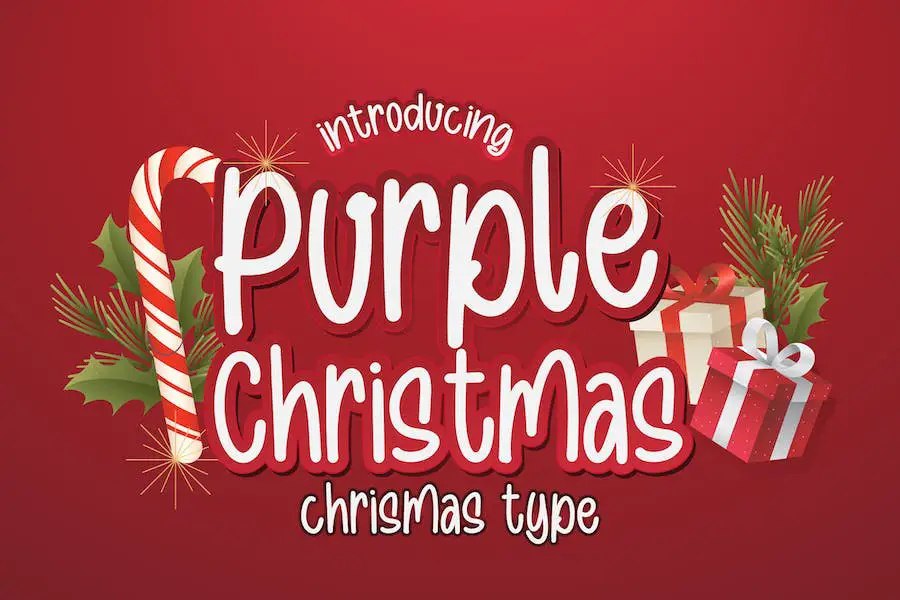
Purple Christmas는 친근하고 우아한 디스플레이 글꼴로 휴일 테마 연하장과 공예 프로젝트에 신선하고 풍부한 느낌을 더합니다. 낭만적인 분위기는 휴가 시즌의 정신을 포착하는 축제 디자인을 만들기에 완벽합니다.
고유한 스타일과 다재다능한 이 글꼴은 우아함과 매력으로 프로젝트를 향상시키려는 그래픽 디자이너에게 탁월한 선택입니다. 퍼플 크리스마스로 깊은 인상을 남길 준비를 하고 휴일의 마법을 구현하는 멋진 디자인을 만드세요.
매직 크리스마스
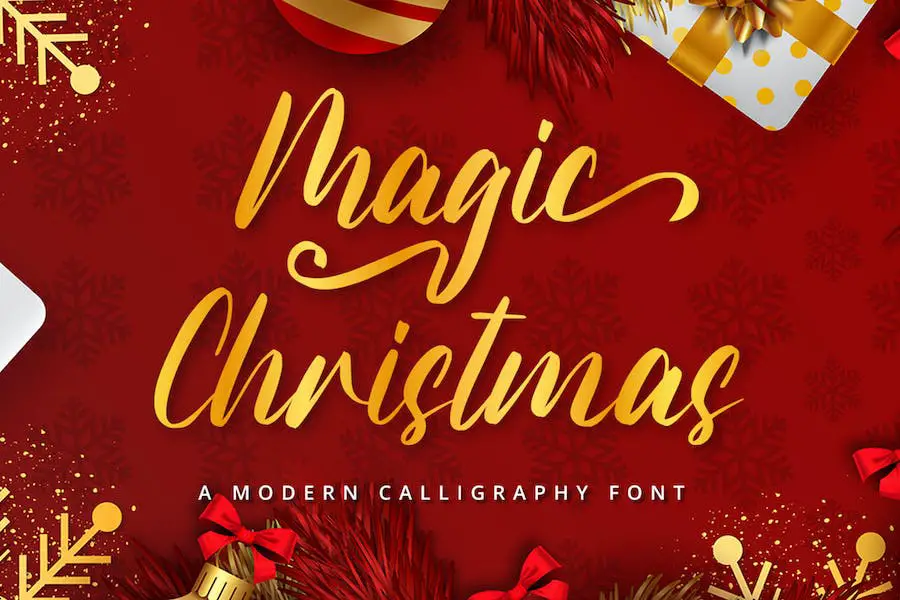
Magic Christmas는 휴가 프로젝트에 우아함을 더해주는 멋진 손글씨 글꼴입니다. 풍부하고 따뜻한 디자인으로 축제 연하장을 만들거나 모든 공예 노력에 아늑한 느낌을 더하는 데 적합합니다.
글꼴은 PUA로 인코딩되어 모든 고유한 글리프 및 스와시에 쉽게 액세스할 수 있습니다. 디자인에 생명을 불어넣을 크리스마스 글꼴을 찾고 있다면 Magic Christmas가 완벽한 선택입니다. 이 아름다운 글꼴로 휴가 창작물을 빛나게 할 준비를 하세요!
간단한 크리스마스
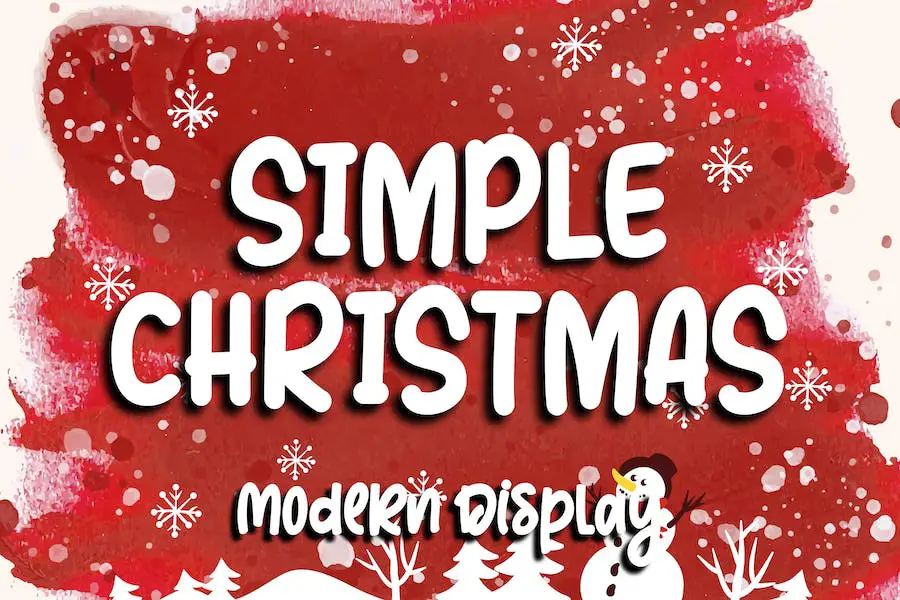
Simple Christmas는 모든 축제 휴가 디자인을 위한 환상적인 글꼴입니다. 대담하고 재미있고 재미있기 때문에 만화 관련 프로젝트, 어린이 게임 또는 사랑스러운 터치가 필요한 창작물에 적합합니다.
이 글꼴을 밝은 색상과 결합하면 아이디어에 생명을 불어넣고 멋진 디자인을 만드는 데 도움이 됩니다. 또한 이 글꼴은 PUA로 인코딩되어 있기 때문에 모든 아름다운 글리프에 매우 쉽게 액세스할 수 있습니다. 그래서 왜 기다려? Simple Christmas로 프로젝트에 휴가 분위기를 더하세요!
크리스마스 우아한
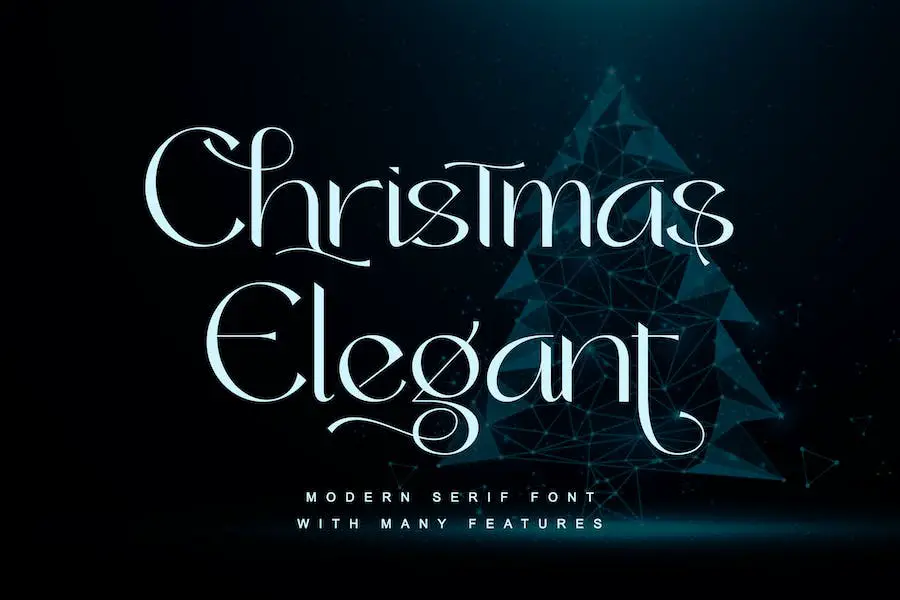
Christmas Elegant는 축제 휴가 디자인에 우아함을 더하는 데 완벽한 멋진 세리프 서체입니다. 모던하고 클래식한 스타일의 이 글꼴은 여러분의 프로젝트를 빛나게 해 줄 것입니다.
독특하고 화려한 분위기에 푹 빠지고 멋진 디자인을 만드는 데 사용할 때 창의력을 발휘하십시오. 또한 글꼴은 PUA로 인코딩되어 모든 글리프에 액세스하고 무한한 가능성을 열 수 있습니다.
명절 카드, 초대장, 심지어 문신 디자인 작업을 하든 Christmas Elegant는 글꼴 컬렉션에 꼭 추가해야 할 필수품입니다. 따라서 이 놀라운 글꼴로 연말 연시 분위기를 퍼뜨릴 준비를 하세요!
크리스마스 희망
Christmas Hopeful은 모든 디자인 요구 사항, 특히 크리스마스 테마 및 공예와 관련된 요구 사항에 완벽한 스크립트 듀오 글꼴입니다. 소셜 미디어 게시물, 인용구, 이미지 오버레이, 슬로건 로고, 포스터, 인쇄물, 웹사이트 배너 등과 같은 다양한 프로젝트에 사용할 수 있습니다.
독특하고 축제적인 스타일의 Christmas Hopeful은 모든 프로젝트에 명절 분위기를 더해줍니다.
글꼴의 속성에는 우아함과 매력을 발산하는 아름다운 스크립트 스타일이 포함됩니다. 그것의 곡선과 복잡한 디테일은 휴가 시즌의 본질을 포착하여 멋진 디자인을 만드는 데 이상적입니다.
크리스마스 인사말 카드를 디자인하든 축제 웹사이트 배너를 디자인하든 Christmas Hopeful은 확실히 프로젝트를 돋보이게 만들 것입니다.
크리스마스 눈송이 딩뱃
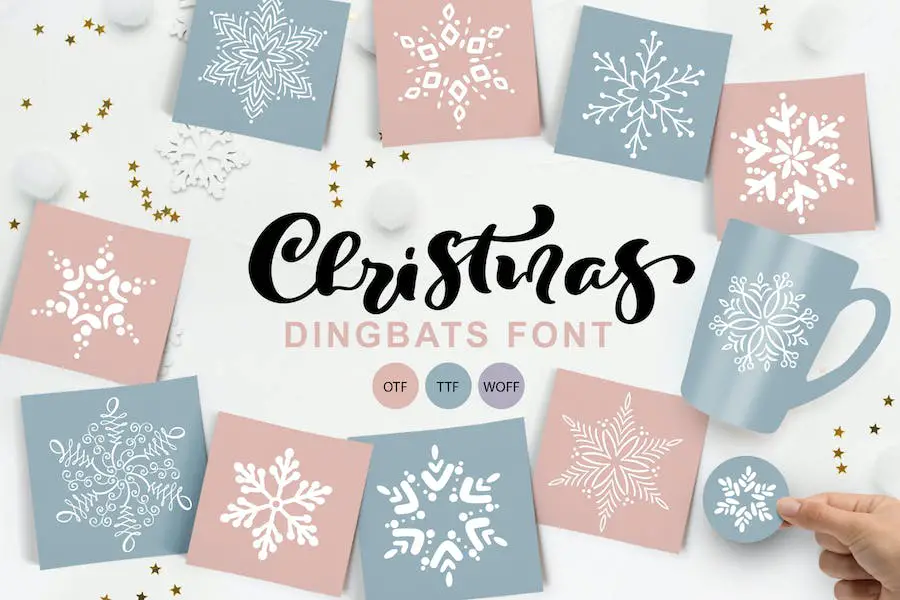
Christmas Snowflake Dingbats는 휴일 테마 프로젝트를 향상시키려는 그래픽 디자이너와 블로거를 위한 환상적인 글꼴입니다.
손으로 그린 낙서 기호로 모든 디자인에 매력을 더합니다. 이 글꼴은 스칸디나비아 또는 휘게 스타일을 수용하는 사람들에게 특히 좋습니다.
Christmas Snowflake Dingbats의 가장 좋은 점 중 하나는 사용 편의성입니다. 이 아름다운 기호에 액세스하기 위해 추가 프로그램이 필요하지 않습니다. 소문자, 대문자 및 숫자를 포함하여 일반 키보드 키에 단순히 매핑됩니다.
글꼴을 설치하고 입력을 시작하고 창의력을 발휘하기만 하면 됩니다!
이 글꼴은 축제 휴일 디자인을 만드는 데 적합합니다. 크리스마스 카드에 명랑한 눈송이 악센트를 추가하거나 독특한 소셜 미디어 그래픽을 만들고 싶다면 Christmas Snowflake Dingbats가 도와드립니다.
덕분에 휴가 분위기를 작업에 쉽게 통합할 수 있습니다.
아버지 크리스마스
Father Christmas는 축제 시즌의 분위기를 담아낸 유쾌한 손글씨 서체입니다. 신선하고 우아한 스타일로 크리스마스 테마 인사말 카드, 브랜딩 자료, 명함, 인용구, 포스터 등을 만드는 데 적합합니다.
이 글꼴은 PUA로 인코딩되어 제공되는 모든 놀라운 글리프 및 스와시에 쉽게 액세스할 수 있습니다. 또한 대체 글리프 및 합자와 같은 다양한 특수 기능이 함께 제공되어 디자인에 창의성을 더할 수 있습니다.
Father Christmas를 사용하면 프로젝트에 명절 분위기를 더할 수 있습니다. 그것의 축제적이고 풍부한 미학은 모든 디자인에 즉시 기쁨과 따뜻함을 더합니다.
사랑하는 사람을 위한 크리스마스 카드를 만들거나 비즈니스를 위한 홍보 자료를 디자인할 때 이 글꼴은 환상적인 선택입니다.
가디건 크리스마스
Cardigan Christmas는 디자인에 사랑과 현대성을 더하는 섬세하고 우아한 손글씨 글꼴입니다. 부드러운 선과 다양한 기준선이 있는 이 글꼴은 제목, 결혼식, 초대장, 서명, 로고 등에 적합합니다.
아름답고 균형 잡힌 캐릭터를 가지고 있어 다양한 디자인에 다용도로 사용할 수 있습니다. 포스터, 배지 또는 브랜딩 자료를 만들 때 Cardigan Christmas는 창의적인 아이디어를 실현할 것입니다. 이 아름다운 글꼴로 프로젝트에 축제 분위기와 스타일리시한 느낌을 더하세요.
카디건 크리스마스를 명절 디자인과 함께 사용하고 크리스마스 시즌 동안 즐겁고 즐거운 분위기를 조성하는 것이 좋습니다. 현대적이고 유려한 스타일은 모든 프로젝트에 우아함과 세련미를 더합니다.
명절 카드, 파티 초대장 또는 기타 계절 자료를 디자인하든 관계없이 이 글꼴은 깊은 인상을 남길 것입니다.
크리스마스 라운지
Christmas Lounge는 일반 및 기울기의 두 가지 스타일로 제공되는 환상적인 디스플레이 서체입니다. 멋진 캐릭터와 독특한 디자인을 갖춘 이 글꼴은 프로젝트를 향상시키는 데 적합합니다.
명함, 포스터, 로고, 잡지, 표지, 배너, 티셔츠, 머리글 또는 대규모 아트워크에 필요한 것이 무엇이든 크리스마스 라운지에서 해결해 드립니다. 모든 디자인에 기쁨을 가져다 줄 다재다능한 글꼴로 축제 분위기를 느껴보세요.
유쾌한 Christmas Lounge 글꼴로 창의력을 발휘하고 프로젝트를 돋보이게 만드세요.
해피 크리스마스 파티
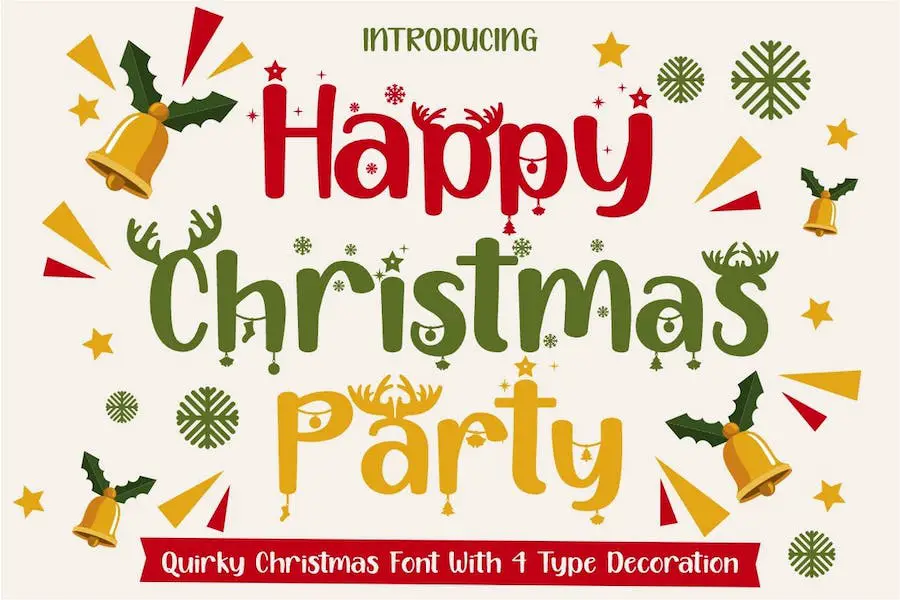
Happy Christmas Party는 홀리데이 시즌을 위해 특별히 디자인된 즐겁고 기발한 디스플레이 글꼴입니다. 일반, 장식, 사슴, 눈, 별 등 5가지 고유한 장식 버전이 있는 이 글꼴은 모든 크리스마스 테마 프로젝트에 완벽한 축제 분위기를 선사합니다.
눈길을 끄는 기프트 카드나 이벤트 초대장을 만들려는 공예가, 독특한 로고타입이나 포장 디자인이 필요한 디자이너라면 이 글꼴을 사용할 수 있습니다.
또한 매우 다재다능하고 다국어를 지원하므로 광범위한 프로젝트에 적합합니다. 해피 크리스마스 파티로 디자인에 크리스마스 마법을 더해보세요!
팔
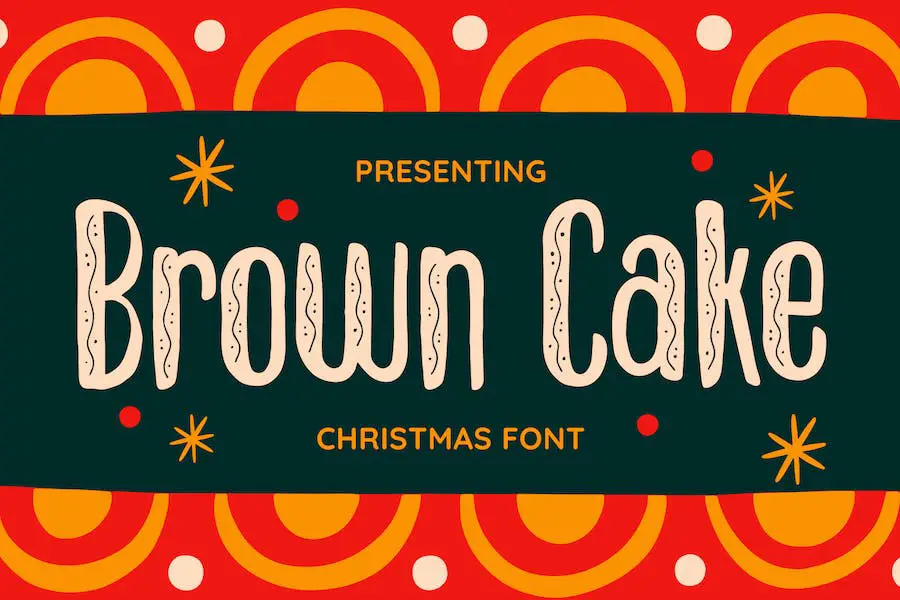
Boom은 휴일 디자인에 축제 분위기를 더하기에 완벽한 멋진 글꼴입니다. 이 글꼴은 매우 다양하며 로고, 브랜딩, 책, 티셔츠, 잡지 등에 사용할 수 있습니다. 시선을 사로잡는 헤드라인과 인사말을 만들기 위한 이상적인 선택입니다.
대문자와 소문자, 숫자와 문장 부호의 조합, 다국어 지원, 개방형 기능을 통해 멋진 디자인을 만드는 데 필요한 모든 도구를 사용할 수 있습니다.
또한 이 글꼴은 다른 글꼴과 아름답게 결합되어 독특하고 응집력 있는 모양을 만들 수 있습니다. Boom으로 프로젝트에 크리스마스 마법을 더할 수 있는 기회를 놓치지 마세요!
사탕
Candy는 그래픽 디자인 프로젝트에 축제 분위기를 더해줄 유쾌한 크리스마스 글꼴입니다. 캘리그라피의 아름다움에서 영감을 받은 이 글꼴은 눈길을 끄는 디스플레이 제작, 티셔츠 디자인, 제작, 인용 부호 제작 및 독특한 로고 제작에 적합합니다.
재미있는 테마와 우아한 스타일을 갖춘 Candy는 휴일 디자인에 장난스럽고 축제적인 분위기를 더할 수 있는 완벽한 선택입니다.
당신이 전문 그래픽 디자이너이거나 휴가철에 솜씨를 발휘하는 것을 즐긴다면, Candy는 당신의 프로젝트에 특별한 터치를 더하기 위한 필수 글꼴입니다.
아나이라
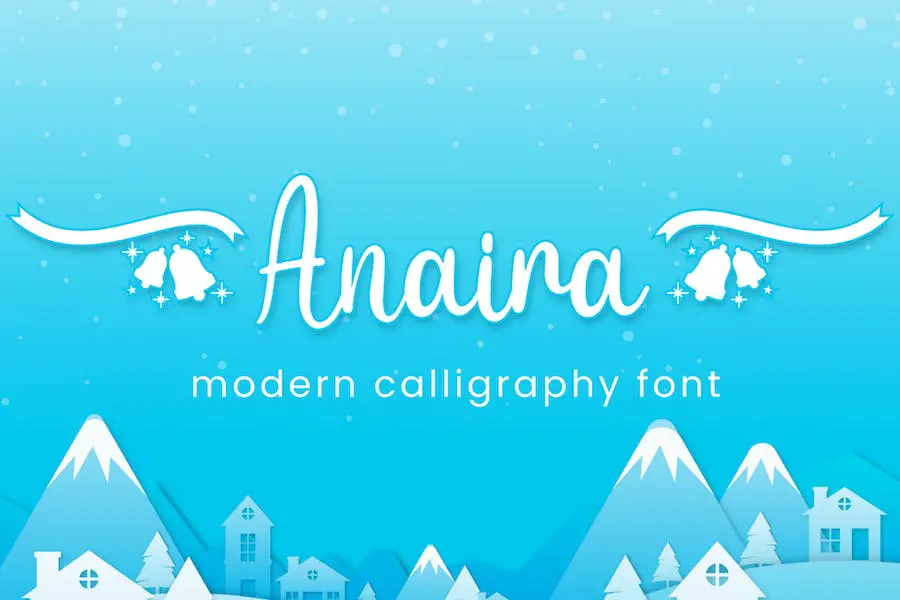
Anaira는 매력적인 벨과 리본 땡땡이 함께 제공되는 아름답고 독특한 손글씨 글꼴입니다. 이 글꼴은 모든 크리스마스 홍보 자료 및 디자인에 이상적입니다.
다양한 기능을 통해 브랜딩, 로고, 초대장, 편지지, 소셜 미디어 게시물, 제품 포장 등을 위한 멋진 그래픽을 만들 수 있습니다.
귀엽고 유쾌한 스타일의 Anaira는 게임 제목, 블로그 디자인, 책 및 표지 제목 및 크리스마스 분위기가 필요한 기타 프로젝트에 적합합니다.
Anaira의 섬세하고 뚜렷한 손글씨는 당신의 시선을 즉시 사로잡을 것입니다. 종과 리본이 특징인 딩뱃 캐릭터는 디자인에 축제 분위기를 더해줍니다.
명절을 주제로 한 로고를 만들거나 크리스마스 세일을 홍보하기 위해 소셜 미디어 게시물을 만들 때 Anaira는 당신의 디자인을 돋보이게 할 독특한 매력을 더할 것입니다.
써니 크리스마스
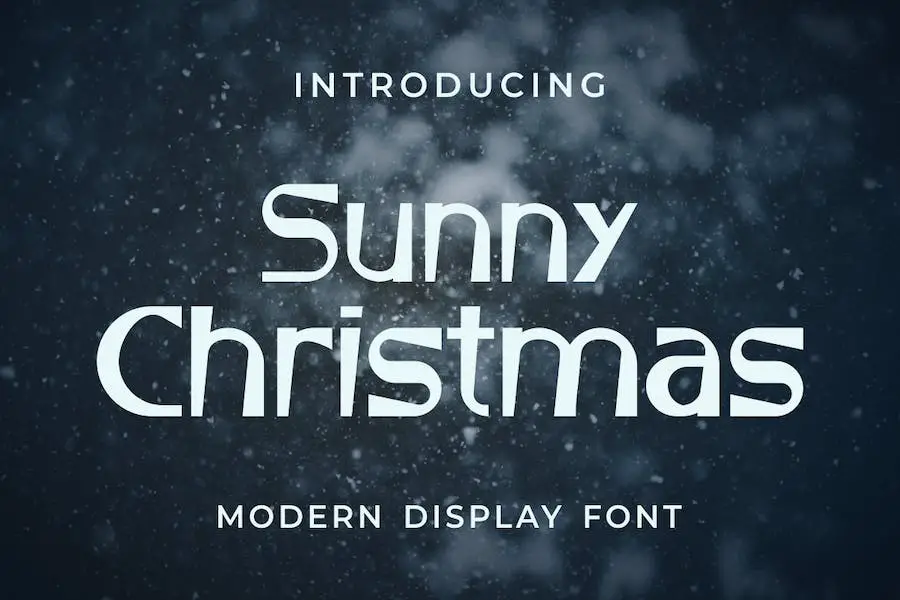
Sunny Christmas는 디자인에 진정성을 더하는 현대적이고 대담한 디스플레이 글꼴입니다. 로고를 작업하든 티셔츠를 인쇄하든 이 글꼴은 모든 브랜딩 프로젝트에 적합합니다. 모든 유형의 컨텍스트에서 눈에 띄고 디자인을 돋보이게 합니다.
Sunny Christmas를 사용하면 휴일 디자인에 축제 분위기와 경쾌한 분위기를 더할 수 있습니다. 독특한 스타일은 크리스마스의 본질을 포착하고 프로젝트에 재미를 더합니다.
이 글꼴은 다재다능하고 다양한 맥락에서 잘 작동하므로 군중에서 눈에 띄는 눈길을 끄는 디자인을 만들 수 있습니다.
캔들파이
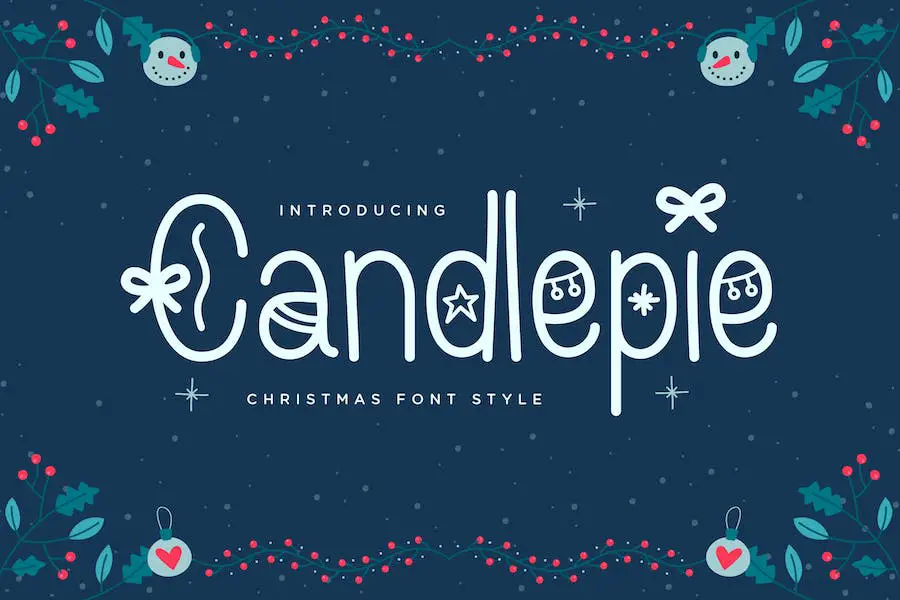
캔들파이는 모든 디자인 프로젝트에 명절 분위기를 더해주는 축제 분위기의 재미있는 크리스마스 글꼴 스타일입니다. 장난기 넘치는 곡선과 기발한 장식으로 인사말 카드, 초대장 및 기타 휴일 테마 디자인을 만드는 데 적합합니다.
이 다재다능한 글꼴은 크리스마스 분위기를 기념하는 디자인에 완벽한 축제 모양과 느낌으로 다양한 설정에서 사용할 수 있습니다. 장난스럽고 경쾌한 디자인으로 기발한 터치가 필요한 디자인에 적합합니다.
명절 연휴 디자인 작업을 하든 그래픽 디자인 프로젝트를 하든, Candlepie는 명절 마법을 더하기 위한 필수 글꼴입니다.
행운의 겨울
디자인에 축제 분위기를 더하고 싶으신가요? 당신의 휴가 프로젝트에 생명을 불어넣을 유쾌한 크리스마스 글꼴인 Lucky Winter만 있으면 됩니다. 대담하고 사실적인 디스플레이를 갖춘 이 글꼴은 로고, 티셔츠 인쇄 등을 포함한 모든 브랜딩 프로젝트에 적합합니다.
다목적이며 다양한 상황에서 사용할 수 있으므로 축제 분위기를 조성하려는 그래픽 디자이너에게 필수품입니다. 그래서 왜 기다려? Lucky Winter로 휴가 분위기를 만끽하고 디자인이 크리스마스 별처럼 밝게 빛나는 것을 확인하세요.
감상적인 느낌
Sentimental Feeling은 크리스마스의 축제 마법을 담아낸 유쾌한 스크립트 글꼴입니다. 1950년대 잡지 사설, 고전 영화, 실제 손으로 쓴 서명에서 영감을 받은 이 글꼴은 휴일 디자인에 복고풍 느낌을 더합니다.
대문자 및 소문자, 숫자, 구두점, 언어 지원, 기호, 대안, 맞춤 합자, 밑줄 및 축제 클립아트의 완전한 세트를 통해 Sentimental Feeling은 완벽한 크리스마스 테마 프로젝트를 만드는 데 필요한 모든 것을 제공합니다.
이 글꼴은 지난 크리스마스의 추억을 불러일으키는 따뜻하고 매력적인 디자인입니다. 부드러운 브러시와 같은 흐름과 인간의 미묘한 결점은 디자인에 매력적이고 개인적인 느낌을 더합니다.
선물 및 문구류 제품, 광고, 제목 또는 기타 무엇을 제작하든 상관없이 Sentimental Feeling은 작업에 휴일 분위기를 불어넣는 데 도움이 될 것입니다.
조이외
Joyeux는 모두 대문자 글꼴과 딩뱃 글꼴을 포함하는 글꼴 모음으로 52개의 사랑스러운 클립아트 삽화가 특징입니다. 이 글꼴은 휴일 프로젝트에 축제의 매력을 더하는 데 적합합니다.
귀엽고 재미있는 디자인으로 Joyeux는 크리스마스를 위한 공예와 디자인을 훨씬 더 재미있게 만들어 줄 것입니다. 그래픽, 연하장 또는 기타 축제 디자인을 만들 때 이 크리스마스 테마 글꼴을 사용하면 창작물에 즐겁고 기발한 요소를 가져올 수 있습니다.
Joyeux와 함께 제공되는 다양한 클립 아트 일러스트레이션으로 상상력을 마음껏 발휘하십시오. 이 유쾌한 글꼴 모음으로 창의력을 발휘하고 휴가 디자인을 진정으로 돋보이게 만드십시오.
눈이 내리는
Snowy는 다재다능하고 축제적인 글꼴로 디자인에 크리스마스 분위기를 더하는 데 적합합니다. 단순하고 장식적인 스타일의 Snowy는 다양한 프로젝트에 이상적입니다.
청첩장을 디자인하든, 인사말 카드를 만들든, 포스터나 인용문을 작업하든 Snowy는 디자인을 향상시키고 축제 분위기를 더할 수 있습니다.
또한 서명, 사진 프로젝트, 브랜딩 자료, 편집 작업 및 엽서에도 적합합니다. Snowy를 사용해보고 크리스마스 테마 디자인을 어떻게 향상시킬 수 있는지 확인하십시오!
산타에게
친애하는 산타는 당신의 디자인 프로젝트에 기쁨을 더해줄 유쾌하고 유쾌한 손글씨 디스플레이 글꼴입니다. 귀엽고 유쾌한 외관은 창의적인 노력을 향상시키는 데 완벽한 선택입니다. 컬렉션에 이 글꼴을 사용하면 가능성이 무한합니다!
제작, 브랜딩 및 장식 프로젝트는 친애하는 산타와 함께 한 단계 더 발전할 것입니다. 청첩장을 디자인하든 블로그를 꾸미든 이 글꼴은 작업에 기발한 매력을 더할 것입니다.
다용도로 사용할 수 있어 로고를 만들거나 아트웍을 구성하거나 가정 장식에 특별한 느낌을 더하는 데 이상적입니다.
그러나 재미는 거기서 멈추지 않습니다! Dear Santa은 비즈니스 자료, 책 표지, 문구류, 마케팅 자료, 심지어 잡지 디자인까지 훌륭한 옵션입니다. 그 독특한 스타일은 청중을 사로잡고 지속적인 인상을 남길 것입니다.
크리스마스 징글
크리스마스 징글은 브랜드 로고와 레터링을 향상시키기 위해 특별히 제작된 글꼴입니다. 크리스마스 카드, 인쇄물, 삽화, 장식 및 모든 크리스마스 테마 디자인을 위한 완벽한 선택입니다.
이 다재다능한 글꼴은 티셔츠, 의류, 홍보 자료, 스포츠 이벤트, 음악 축제 및 영감을 주는 인용구에도 적합합니다. 크리스마스 징글을 사용하면 모든 프로젝트나 특별 이벤트에 축제 분위기를 더할 수 있습니다. 이 재미있고 스타일리시한 글꼴로 창의력을 발휘하고 크리스마스 분위기를 전하세요.
힘의 겨울
Strength Winter – 캘리그래피 크리스마스 폰트는 독특한 손글씨를 담은 폰트로 다양한 디자인 프로젝트에 적합합니다.
광고, 브랜딩, 웨딩 디자인 또는 제품 포장 작업을 하든 이 글꼴은 창의적인 노력에 축제 분위기를 더해줍니다.
우아한 분위기로 초대장, 편지지 및 소셜 미디어 게시물을 위한 멋진 비주얼을 만들기에도 완벽합니다. Strength Winter의 다재다능함 덕분에 손글씨 터치가 필요한 모든 프로젝트를 향상시킬 수 있습니다.
크리스마스
크리스마스는 그래픽 디자인 프로젝트에 축제 분위기를 더해주는 다재다능한 글꼴입니다. 로고, 배지, 전단지, 포스터 등을 만드는 데 적합합니다. 독특한 스타일과 휴일 테마 디자인 요소로 디자인의 전체적인 모양과 느낌을 향상시킬 수 있습니다.
휴일을 주제로 한 홍보 자료를 작업하거나 단순히 디자인에 약간의 크리스마스 정신을 불어넣고 싶을 때 크리스마스는 필요한 글꼴입니다.
다양한 글리프와 문자는 무한한 가능성을 허용하므로 프로젝트에 특별한 터치를 추가하려는 모든 그래픽 디자이너에게 필수품입니다.
크리스마스 북유럽
크리스마스 노르딕은 휴일 디자인에 축제 느낌을 더하기에 완벽한 겨울 핸드메이드 글꼴입니다. 손으로 그린 이 글꼴은 디자이너, 블로거 및 낙서, 스칸디나비아 또는 휘게 스타일을 사랑하는 모든 사람을 위한 아름다운 도구입니다.
일반키보드와 볼드키에 매핑되어 별도의 프로그램 없이도 쉽게 사용하실 수 있습니다. 글꼴을 설치하고 입력하고 창의력을 발휘하십시오!
손으로 그린 독특한 스타일의 Christmas Nordic은 모든 프로젝트에 개인화되고 매력적인 터치를 더합니다. 연휴 카드를 디자인하든, 소셜 미디어 그래픽을 만들든, 블로그 게시물을 작성하든 이 글꼴은 디자인에 생명을 불어넣을 것입니다.
현대적인 디스플레이 디자인은 휴가 시즌의 본질을 포착하여 이목을 끌고 축제 분위기를 확산시키는 데 적합합니다.
니코 라우스
Nico Laus는 크리스마스의 정신을 담아낸 즐겁고 축제적인 디스플레이 글꼴입니다. 귀엽고 장난스러운 스타일로 디자인된 이 글꼴은 어린이 책과 제품에 대한 매력적인 디자인을 만드는 데 적합합니다.
다국어 지원을 제공하므로 서유럽, 중부 및 동유럽 언어로 된 광범위한 프로젝트에 액세스할 수 있습니다.
독특한 글자로 Nico Laus는 휴가 창작물에 행복을 더하고 그래픽 디자인 프로젝트에 기쁨과 환호를 선사합니다. 당신의 디자인을 돋보이게 해 줄 이 매력적인 크리스마스 글꼴로 축제 시즌을 맞이하세요.
크리스마스 준 딩뱃
독특하고 다양한 크리스마스 장식 요소 모음인 Christmas June Dingbat 글꼴을 소개합니다. 대문자와 소문자, 숫자, 구두점 및 기호를 포함하여 총 96개의 글리프가 있는 이 글꼴은 휴일 디자인에 축제 분위기를 더하는 데 적합합니다.
휴일 프로모션을 위한 그래픽을 만들거나 크리스마스 카드를 디자인할 때 이 글꼴은 확실히 프로젝트를 향상시키고 돋보이게 할 것입니다. 다양한 캐릭터를 통해 눈길을 끄는 디자인을 만드는 데 필요한 모든 장식 요소를 갖게 됩니다.
Christmas June Dingbat 글꼴로 휴일 분위기를 만끽하고 그래픽 디자인 프로젝트를 향상시키십시오. 연말연시 디자인과 Canva 사용자에게 완벽한 이 글꼴은 작품에 생명을 불어넣을 것입니다.
크리스마스 코브
Christmas Cove는 휴가 시즌의 마법을 포착하는 다목적 크리스마스 글꼴입니다. 클래식한 디자인으로 그래픽 디자인 프로젝트에 축제 분위기를 더하는 데 적합합니다.
이 글꼴에는 숫자, 구두점 및 다국어 문자와 같이 필요한 모든 필수 요소가 포함되어 있습니다.
또한 제공된 합자를 사용하여 청중에게 깊은 인상을 줄 독특하고 매혹적인 디자인을 만들 수 있습니다. 크리스마스 카드, 연휴 배너 또는 축제 소셜 미디어 게시물을 디자인하든 관계없이 Christmas Cove가 도와드립니다.
그 기발하고 매혹적인 스타일은 당신의 프로젝트에 생명을 불어넣고 돋보이게 할 것입니다. 따라서 디자인에 축제 분위기를 더할 수 있는 완벽한 글꼴을 찾고 있다면 Christmas Cove만 있으면 됩니다.
아름답고 매혹적인 휴일 테마 그래픽을 만들기 위한 이상적인 선택입니다.
따뜻한 크리스마스
따뜻한 크리스마스는 어떤 디자인에도 고전적인 우아함을 더해주는 환상적인 Handwritten Script 글꼴입니다. 매력적이고 다재다능한 스타일로 소박한 농가 테마부터 트렌디한 보헤미안 디자인에 이르기까지 다양한 룩을 연출하기에 완벽합니다.
여성스러운 감각으로 따뜻한 크리스마스는 이벤트, 웨딩 프로젝트, 패션 디자인, 의류 디자인 등에 탁월한 선택입니다. 특정 프로젝트에만 국한되지 않습니다. 로고, 브랜딩, 잡지 레이아웃, 소셜 미디어 게시물 및 광고에 사용할 수 있습니다.
글꼴 컬렉션에 따뜻한 크리스마스를 추가하면 독창성을 높이고 디자인에 축제 분위기를 더할 수 있습니다.
최고의 무료 크리스마스 글꼴
휴일 디자인 프로젝트에 축제 분위기를 더하고 싶으신가요? 크리스마스를 위한 최고의 무료 글꼴을 엄선한 것보다 더 이상 보지 마십시오! 당신의 창작물을 즐겁고 밝게 만들어 줄 완벽한 서체를 찾아보세요.
크리스마스
크리스마스 글꼴은 프로젝트에 축제 분위기를 더하려는 모든 그래픽 디자이너에게 꼭 필요한 글꼴입니다. 최고의 옵션 중 하나는 Jacky Hernandes의 크리스마스 글꼴입니다.
이 글꼴은 개인적인 용도로 무료로 사용할 수 있을 뿐만 아니라 휴일 디자인에 완벽한 다양한 특성을 제공합니다.
크리스마스 글꼴을 사용하면 프로젝트에 크리스마스 분위기를 즉시 연출할 수 있습니다. 이 글꼴의 우아하고 유쾌한 디자인은 크리스마스의 정신을 포착하고 모든 디자인에 즐거운 요소를 더합니다.
크리스마스 카드, 파티 초대장 또는 소셜 미디어 그래픽 작업을 할 때 이 글꼴은 전체 디자인을 향상시키고 진정으로 빛나게 합니다.
크리스마스 스파클
Christmas Sparkle은 Mans Greback이 만든 유쾌한 글꼴로 모든 휴일 디자인 프로젝트에 축제 분위기를 더합니다. 우아하고 반짝이는 디테일이 있는 이 글꼴은 크리스마스 카드, 파티 초대장 또는 소셜 미디어 그래픽에 마법을 더하는 데 적합합니다.
이 글꼴은 반짝이는 크리스마스 전구를 연상시키는 아름답게 만들어진 글자를 특징으로 합니다. 자유롭게 흐르는 필기체 스타일은 휴가 시즌의 정신을 포착하여 디자인에 따뜻함과 즐거움을 선사합니다.
휴일 테마 로고, 포스터 또는 웹사이트 배너를 만들 때 Christmas Sparkle은 즉시 축제의 매력으로 디자인을 향상시킵니다.
다재다능함으로 개인 및 상업 프로젝트 모두에 사용할 수 있으므로 모든 그래픽 디자이너의 글꼴 컬렉션에 추가할 가치가 있습니다.
메리 크리스마스 컬러
Merry Christmas Color는 Mans Greback이 디자인한 축제용 글꼴입니다. 디자인에 연말연시의 분위기를 더하기에 완벽한 비상업용 프리웨어 글꼴입니다.
재미있고 유쾌한 스타일의 메리 크리스마스 컬러는 홀리데이 시즌에 시선을 사로잡는 그래픽을 만드는 데 이상적입니다.
인사말 카드, 초대장 또는 소셜 미디어 게시물을 디자인하든 이 글꼴은 확실히 프로젝트에 축제 분위기를 더할 것입니다. 고유한 속성과 생생한 색상으로 인해 창작물에 즐거운 터치를 더하려는 그래픽 디자이너에게는 필수 아이템입니다.
그렇다면 이번 휴가 시즌에 메리 크리스마스 색상을 사용해보고 디자인을 빛나게 해보는 건 어떨까요? 축제 휴일 디자인 및 그래픽 디자인 프로젝트를 위한 이 크리스마스 글꼴로 휴일 분위기에 빠져보세요.
메리 크리스마스
Mans Greback의 Merry Christmas는 휴일 디자인 프로젝트에 축제 분위기를 더하기에 완벽한 환상적인 크리스마스 글꼴 컬렉션입니다. 이 비상업용 프리웨어 글꼴 패키지는 그래픽 디자인을 향상시키는 다양한 옵션을 제공합니다.
메리 크리스마스와 함께 연말연시의 분위기를 담은 다양한 글꼴을 만나보실 수 있습니다. 각 글꼴에는 고유한 스타일과 감각이 있어 프로젝트에 가장 적합한 글꼴을 선택할 수 있습니다.
우아한 스크립트 글꼴에서 재미있고 기발한 옵션에 이르기까지 모든 디자인 미학을 위한 무언가가 있습니다.
메리 크리스마스의 가장 큰 장점 중 하나는 사용하기 쉽다는 것입니다. 글꼴은 다양한 디자인 소프트웨어와 호환되므로 프로젝트에 간단하게 통합할 수 있습니다.
연하장, 파티 초대장 또는 소셜 미디어 그래픽을 만들 때 이 글꼴을 사용하면 축제 분위기를 더할 수 있습니다.
크리스마스
Christmas by WDfontFreeware는 프로젝트를 향상시키려는 그래픽 디자이너에게 완벽한 휴일 글꼴 컬렉션입니다. 이 크리스마스 글꼴은 모든 디자인에 명절 분위기와 축제 분위기를 더해줍니다.
크리스마스와 함께 연말연시의 진수를 담아낸 다양한 폰트를 만나보실 수 있습니다. 우아한 필기체부터 대담하고 유쾌한 서체까지, 이 컬렉션은 모든 디자인 스타일에 맞는 다양한 옵션을 제공합니다.
크리스마스 카드, 포스터 또는 소셜 미디어 그래픽 작업을 할 때 이 글꼴을 사용하면 특별한 터치를 더할 수 있습니다.
이 글꼴은 무료로 제공되며 비상업적 프로젝트에 사용할 수 있습니다. 다운로드 및 설치가 쉽기 때문에 디자이너가 작업에 빠르게 통합할 수 있어 편리합니다.
크리스마스
Christmas by WinarkoFreeware는 프로젝트에 명절 분위기를 더하고자 하는 그래픽 디자이너에게 완벽한 축제 명절 글꼴 모음입니다. 이 글꼴 컬렉션은 각각 고유한 매력과 개성을 지닌 다양한 스타일을 제공합니다.
크리스마스 글꼴을 사용하면 휴가 시즌의 본질을 포착하는 눈길을 끄는 디자인을 만들 수 있습니다. 명절 카드, 파티 초대장 또는 소셜 미디어 그래픽을 디자인하든 관계없이 이 글꼴을 사용하면 축제와 즐거운 느낌으로 프로젝트에 생명을 불어넣을 수 있습니다.
세련미를 발산하는 우아한 스크립트 글꼴부터 크리스마스의 재미와 흥분을 포착하는 장난스럽고 기발한 글꼴에 이르기까지 이 컬렉션은 모든 스타일과 디자인 요구 사항을 충족합니다.
각 글꼴은 명확성과 가독성을 보장하기 위해 세심하게 제작되어 크고 작은 텍스트 요소 모두에 다용도로 사용할 수 있습니다.
크리스마스
Christmas는 휴일 테마의 그래픽 디자인 프로젝트를 향상시키기 위해 디자인된 글꼴 모음입니다. 스크래치 글꼴로 만든 이 프리웨어 글꼴 팩은 큰 비용을 들이지 않고도 디자인에 축제 분위기를 더하는 데 적합합니다.
다양한 스타일과 옵션을 갖춘 이 크리스마스 글꼴은 여러분의 프로젝트에 축제 분위기를 더해줄 것입니다. 크리스마스 카드, 파티 초대장 또는 휴일 테마 웹사이트에서 작업할 때 이 글꼴을 사용하면 시각적으로 매력적이고 전문적인 디자인을 만들 수 있습니다.
크리스마스 글꼴 팩에는 우아하고 기발한 것부터 대담하고 장난스러운 것까지 다양한 스타일이 포함되어 있습니다. 지팡이 사탕 글자, 눈송이 장식, 크리스마스 트리 악센트와 같은 옵션을 사용하여 휴일 분위기를 디자인에 쉽게 통합할 수 있습니다.
고전적이고 전통적인 글꼴을 찾고 있든, 더 현대적이고 독특한 글꼴을 찾고 있든, 이 컬렉션에는 모든 것이 있습니다.
안녕 크리스마스
Hi Christmas by Typhoon Type – Suthi Srisopha는 모든 그래픽 디자인 프로젝트에 축제 분위기를 더해줄 환상적인 크리스마스 글꼴 컬렉션입니다. 이 프리웨어 글꼴 패키지는 큰 비용을 들이지 않고 휴일 테마 작품을 향상시키려는 그래픽 디자이너에게 적합합니다.
아름답게 디자인된 다양한 글꼴로 Hi Christmas를 사용하면 디자인에 기쁨과 환호를 더할 수 있습니다.
Hi Christmas의 가장 좋은 점 중 하나는 비상업적 용도로 완전히 무료라는 것입니다. 즉, 사랑하는 사람을 위한 크리스마스 카드를 만드는 것과 같은 개인 프로젝트나 비영리 목적으로 이러한 글꼴을 사용할 수 있습니다.
Typhoon Type – Suthi Srisopha에서 디자이너가 라이선스 비용에 대한 걱정 없이 자신의 작업에 크리스마스 마법을 더할 수 있도록 하는 후한 제안입니다.
크리스마스벳
Christmabet은 모든 휴일 디자인과 그래픽 프로젝트에 축제 분위기를 더해줄 환상적인 크리스마스 글꼴입니다. Cat Neligan에서 개발한 이 프리웨어 글꼴은 창의적인 작업에 크리스마스 테마 분위기를 더하는 데 적합합니다.
인사말 카드, 초대장 또는 소셜 미디어 게시물을 디자인하든, Christmabet이 도와드립니다.
독특하고 기발한 서체를 통해 Christmabet은 휴가 시즌의 본질을 포착합니다. 각 캐릭터는 눈송이, 사탕 지팡이, 크리스마스 장식품과 같은 전통적인 크리스마스 이미지의 요소를 통합하도록 복잡하게 디자인되었습니다.
글꼴의 장난스럽고 즐거운 미학은 모든 디자인을 즉시 경쾌하고 즐거운 걸작으로 바꿔줍니다.
크리스마스 날
Billy Argel Fonts의 Christmas Day는 그래픽 디자인 프로젝트에 연말 분위기를 더하기에 완벽한 축제 글꼴 컬렉션입니다. 이 비상업용 프리웨어 글꼴 팩은 스타일리시하고 사용하기 재미있는 크리스마스에서 영감을 받은 다양한 글꼴을 제공합니다.
Christmas Day는 다양한 글꼴을 제공할 뿐만 아니라 각 글꼴의 품질이 우수하고 사용하기 쉽습니다. 글꼴은 가독성이 뛰어나고 정교하게 제작되어 더 복잡한 디자인에서도 텍스트가 눈에 띄고 가독성을 유지합니다.
또한 글꼴은 다양한 디자인 소프트웨어와 호환되므로 기존 프로젝트에 쉽게 통합할 수 있습니다.
빨간 크리스마스
Red Christmas by Typhoon Type – Suthi Srisopha는 그래픽 디자인 프로젝트에 크리스마스 분위기를 더하는 데 적합한 축제용 글꼴입니다. 이 프리웨어 글꼴은 축제적이고 즐거운 모습으로 프로젝트를 향상시키려는 그래픽 디자이너에게 이상적입니다.
Red Christmas의 두드러진 특징 중 하나는 다양성입니다. 크리스마스 테마 포스터, 연하장 또는 축제 소셜 미디어 그래픽을 만들 때 이 글꼴을 디자인에 쉽게 통합하여 축제 분위기와 시선을 사로잡는 매력을 더할 수 있습니다.
대담하고 관심을 끄는 특성으로 인해 귀하의 메시지를 보고 기억할 수 있습니다.
Red Christmas의 또 다른 큰 특징은 비상업적 용도의 프리웨어 글꼴로 사용할 수 있다는 것입니다. 즉, 디자이너는 제한이나 라이선스 비용 없이 이 글꼴을 다운로드하여 사용할 수 있으므로 휴가 디자인을 향상시키기 위한 저렴하고 접근 가능한 선택이 됩니다.
크리스마스를 위해
For Christmas는 휴일 디자인과 그래픽 프로젝트에 축제 분위기를 더해줄 멋진 크리스마스 글꼴 컬렉션입니다. Jadatype에서 만든 이 프리웨어 글꼴 팩은 비상업적 용도에 적합합니다.
For Christmas 글꼴 팩은 대담하고 장식적인 서체를 포함하여 다양한 글꼴 스타일을 제공하므로 쉽게 창의력을 표현하고 디자인을 개인화할 수 있습니다.
시선을 사로잡는 헤드라인이 있는 멋진 휴일 테마 포스터를 만들거나 웹 사이트의 탐색 메뉴에 축제 느낌을 추가한다고 상상해 보십시오. 이 컬렉션의 가능성은 무궁무진합니다.
크리스마스 이야기
Christmas Story는 fikryalstudio에서 만든 프리웨어 글꼴로, 휴일 디자인에 축제 분위기를 더하는 데 적합합니다. 독특하고 기발한 스타일로 이 글꼴은 모든 프로젝트에 크리스마스 분위기를 선사할 것입니다.
크리스마스 카드, 초대장 또는 기타 명절 테마의 그래픽 디자인 작업을 할 때 Christmas Story는 창의력을 향상할 수 있는 다양한 캐릭터와 장식 요소를 제공합니다.
이 글꼴은 개인용 및 비상업용으로 무료이므로 전문가와 애호가 모두에게 훌륭한 옵션입니다. 크리스마스 스토리의 즐겁고 밝은 매력으로 당신의 디자인을 빛나게 하세요.
크리스마스 굴뚝
Christmas Chimney는 그래픽 디자인 프로젝트에 명절 분위기를 더하기에 완벽한 축제 글꼴입니다. 이 비상업용 프리웨어 글꼴은 letterara에서 제공하며 휴가 시즌 동안 디자인을 돋보이게 만들어 줄 것입니다.
Christmas Chimney의 가장 좋은 점 중 하나는 다양성입니다. 지나치게 장식적이거나 읽기 어렵지 않아 다양한 프로젝트에 적합합니다. 전문 그래픽 디자이너이든 막 시작하든 상관없이 이 글꼴은 사용하기 쉽고 디자인에 생명을 불어넣을 것입니다.
이 글꼴의 또 다른 훌륭한 기능은 무료로 사용할 수 있다는 것입니다. 라이센스 제한이나 상업적 제한에 대해 걱정할 필요가 없습니다. Christmas Chimney는 비상업적 용도뿐만 아니라 개인 프로젝트에 적합합니다. 추가 비용 없이 휴가 분위기를 확산하세요!
자주 묻는 질문
크리스마스 글꼴은 인사말 카드, 초대장, 배너 등과 같은 다양한 크리스마스 관련 디자인에 축제 분위기를 더하는 데 사용되는 특수 서체 또는 글자 스타일입니다.